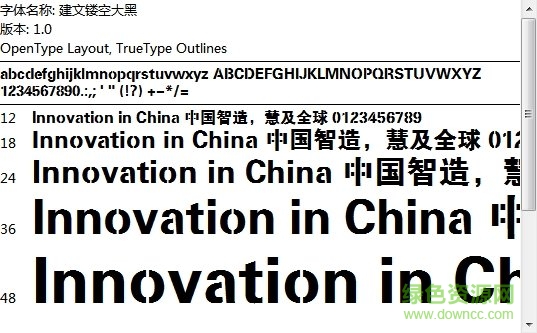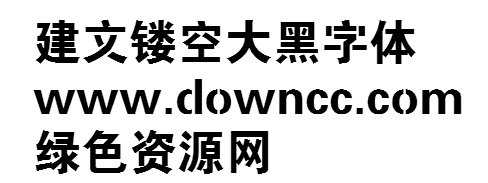
建文鏤空大黑字體是一款效果十分出色的鏤空字體,在部分漢字和英文字母上做出了處理,讓文字形散而神不散,更加獨(dú)特顯眼,如果你喜歡,不妨來綠色資源網(wǎng)免費(fèi)體驗吧!
鏤空字體給人一種格式大氣、造型突出的莊重體驗,鏤空的設(shè)計讓其更具層次感,在一些平面設(shè)計上,讓字體擁有不同的顏色或重疊,給人比較醒目的視覺效果。
建文鏤空字體讓用戶直接使用,可以免去用photoshop、word等設(shè)計的復(fù)雜過程,形態(tài)因加黑設(shè)計而顯得深沉,線條筆直而顯得美觀,讓你的包裝設(shè)計更加語種不同。